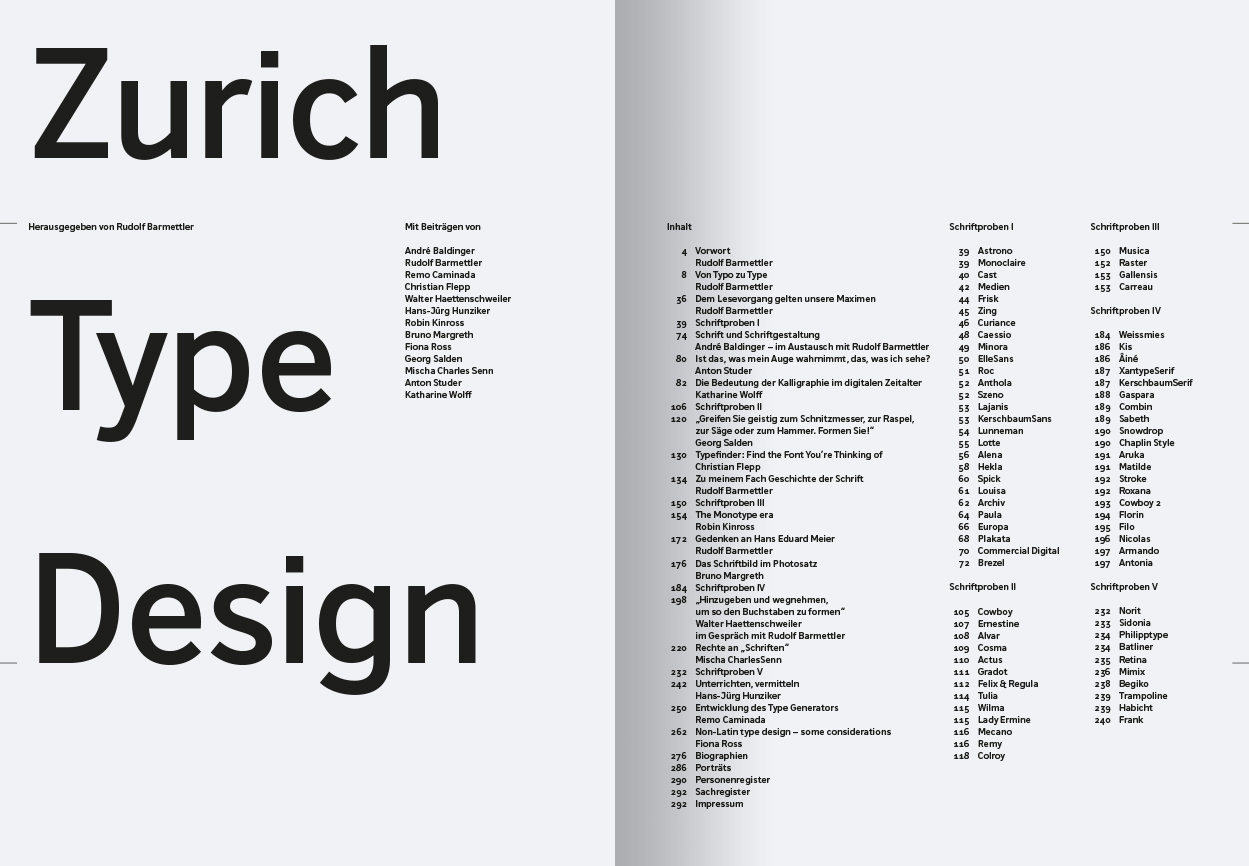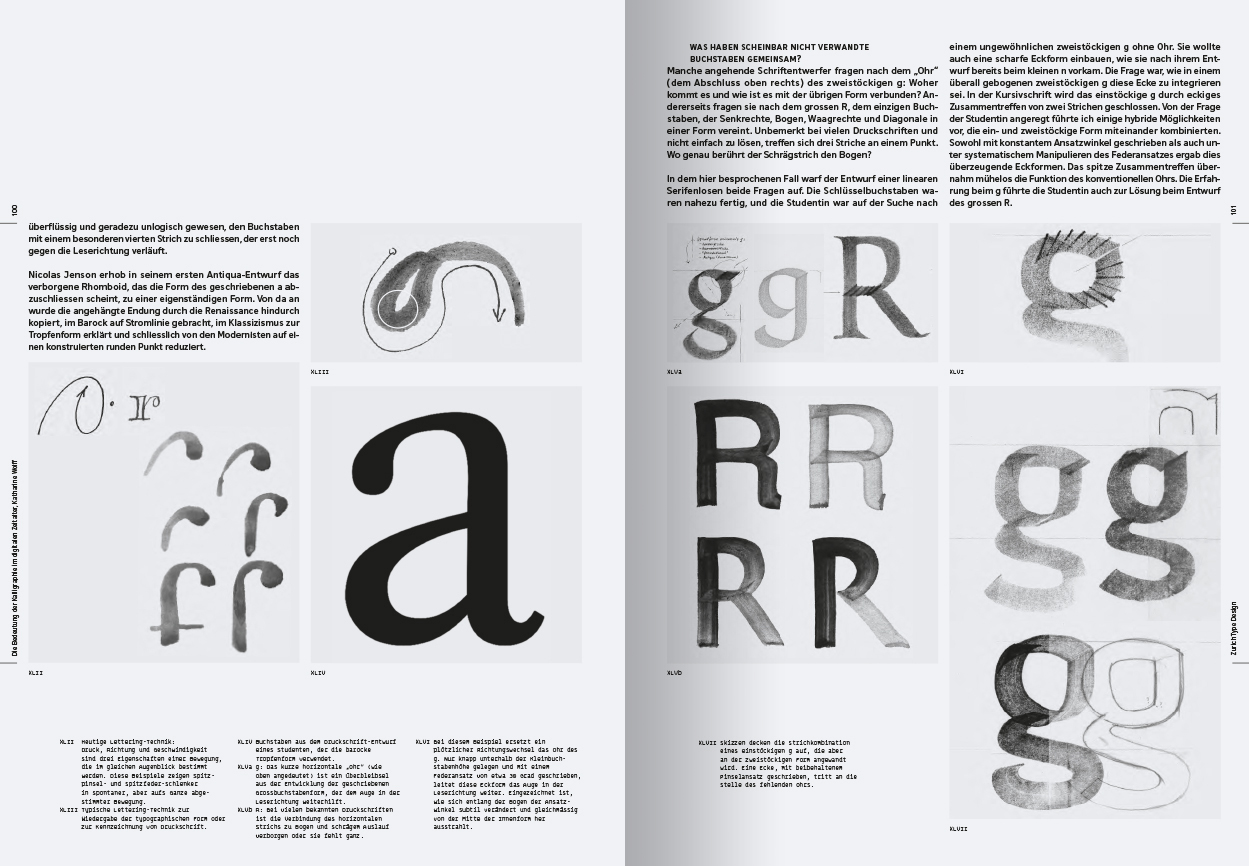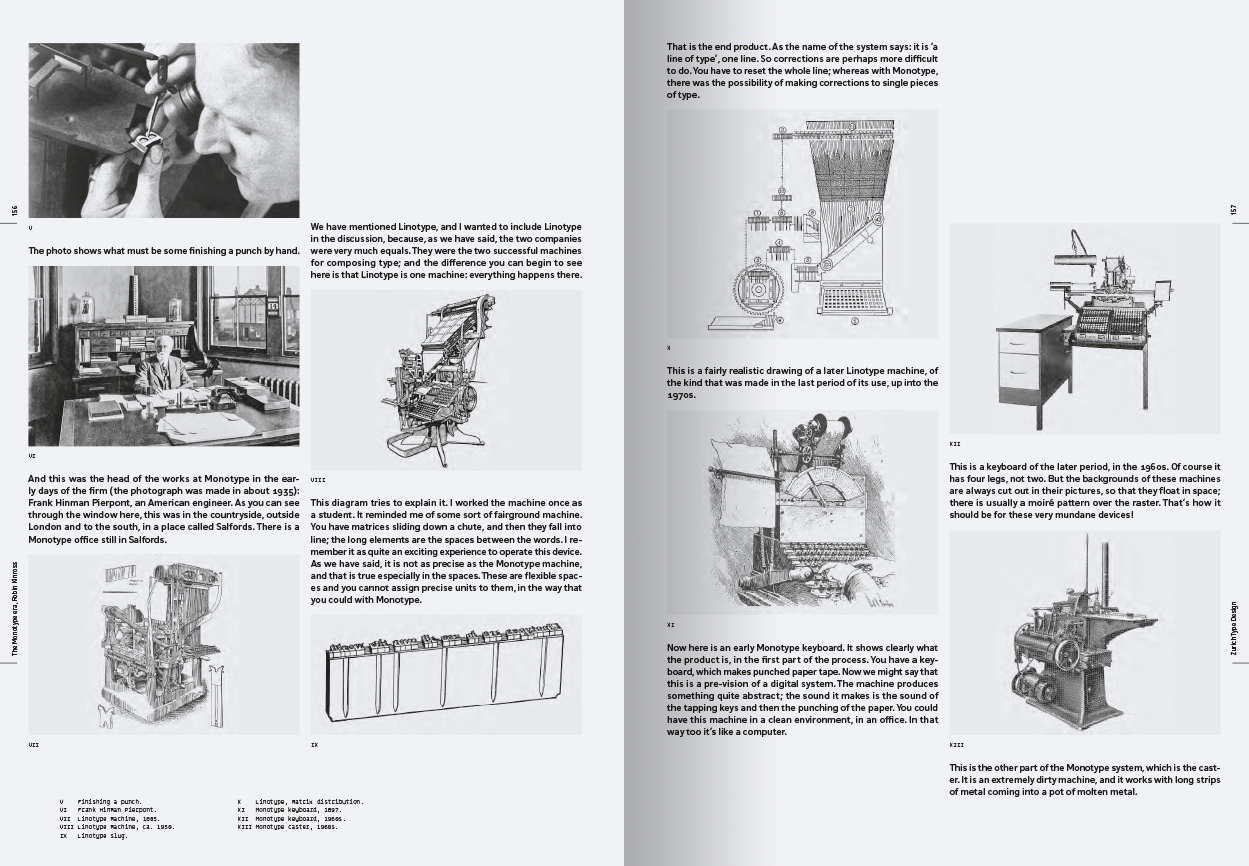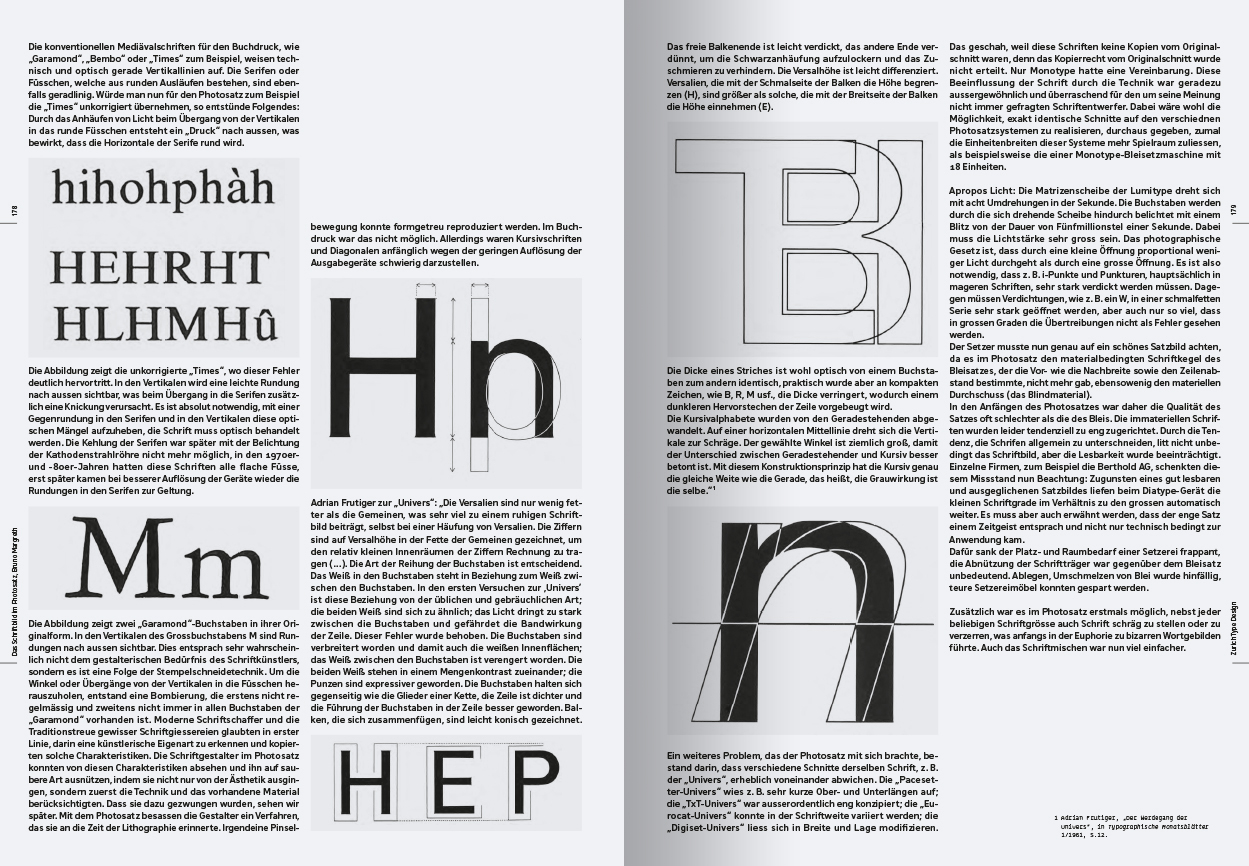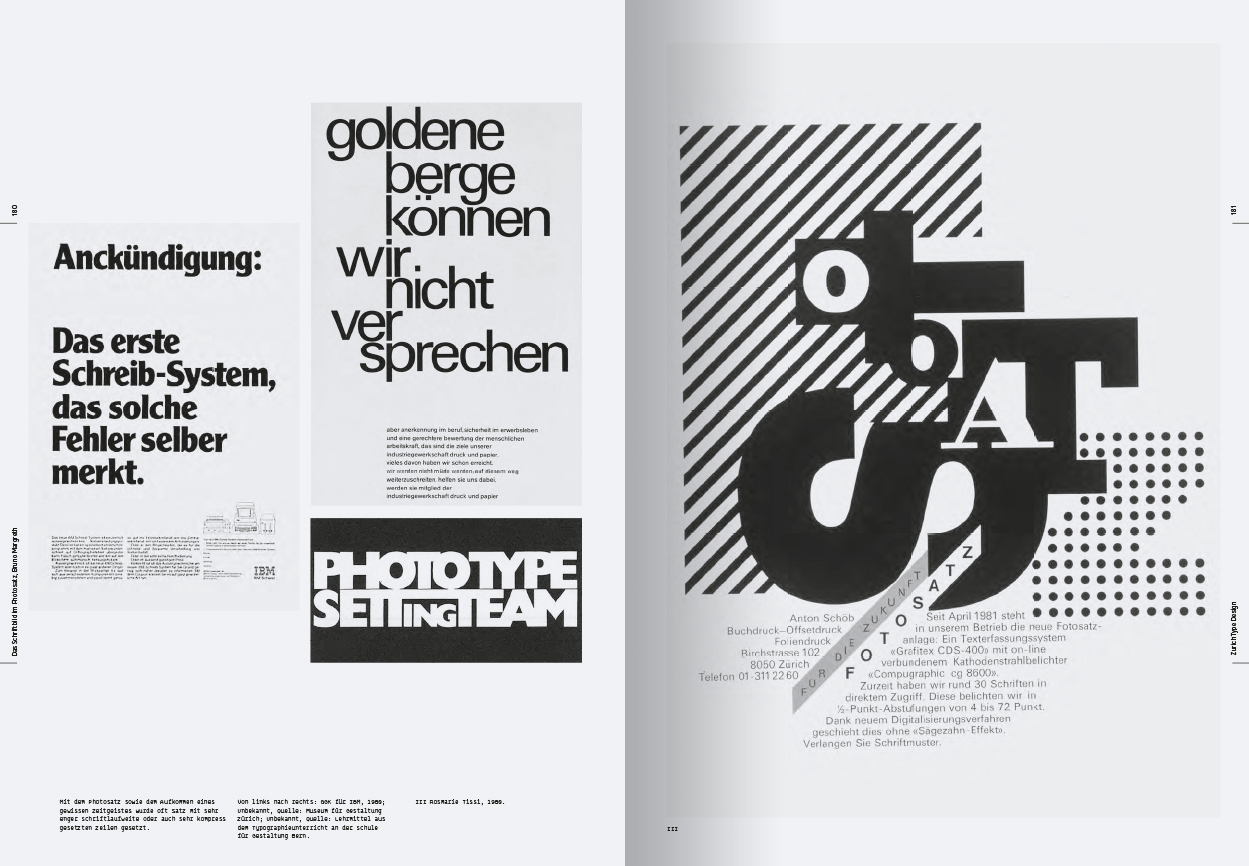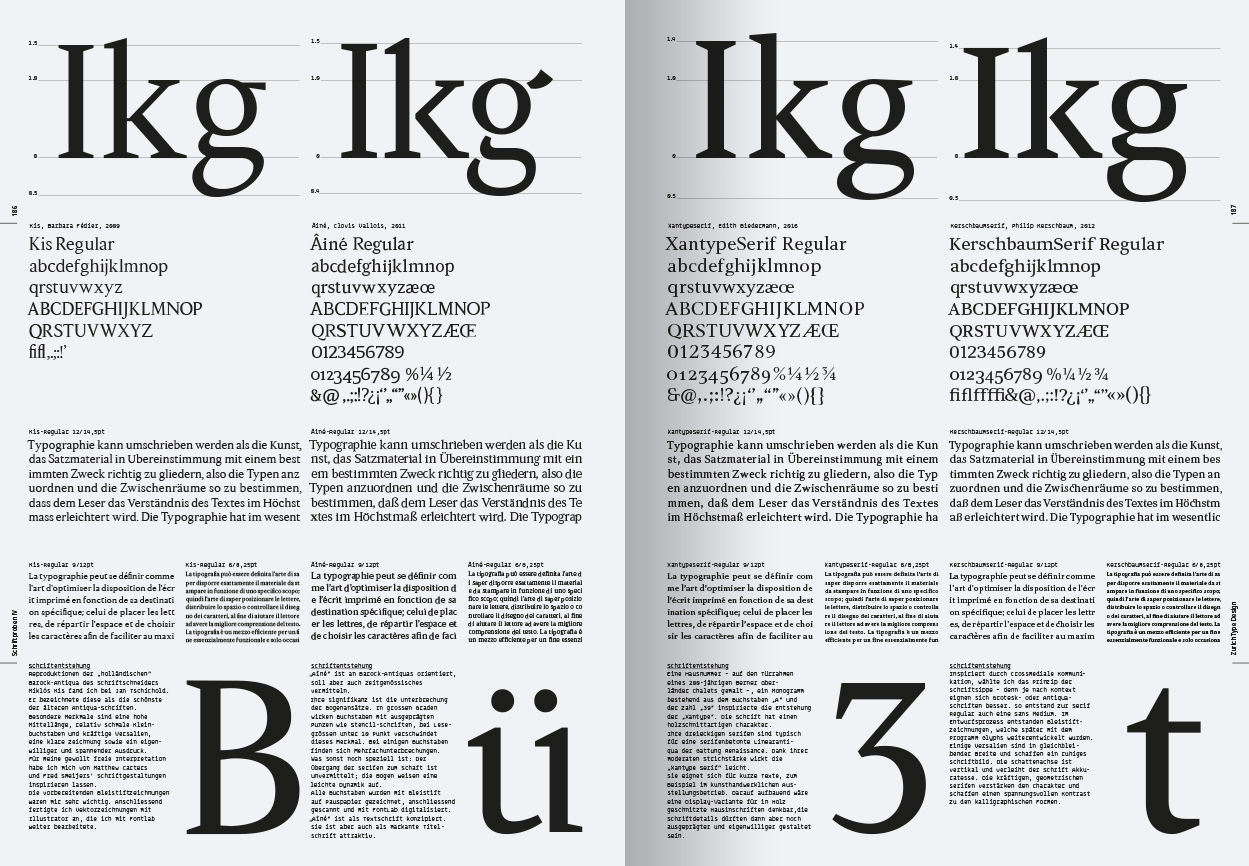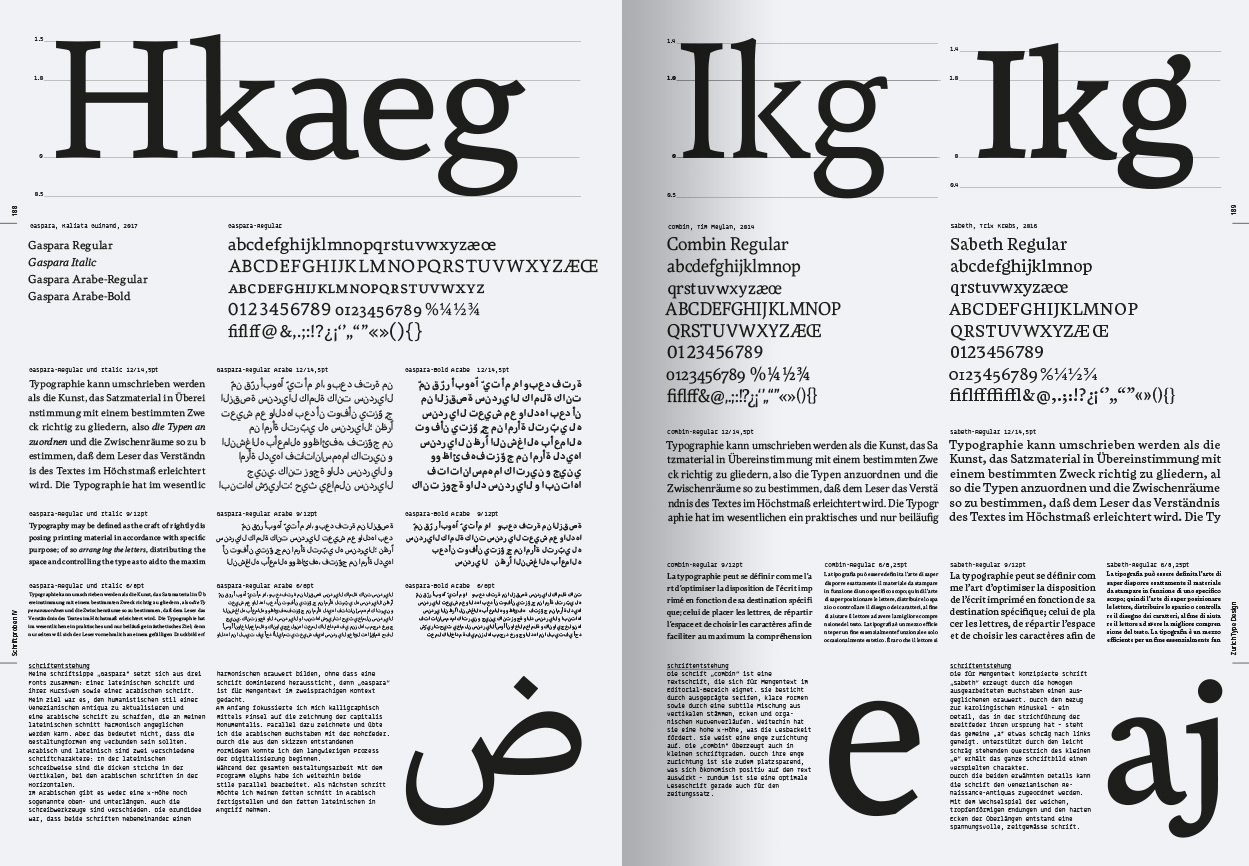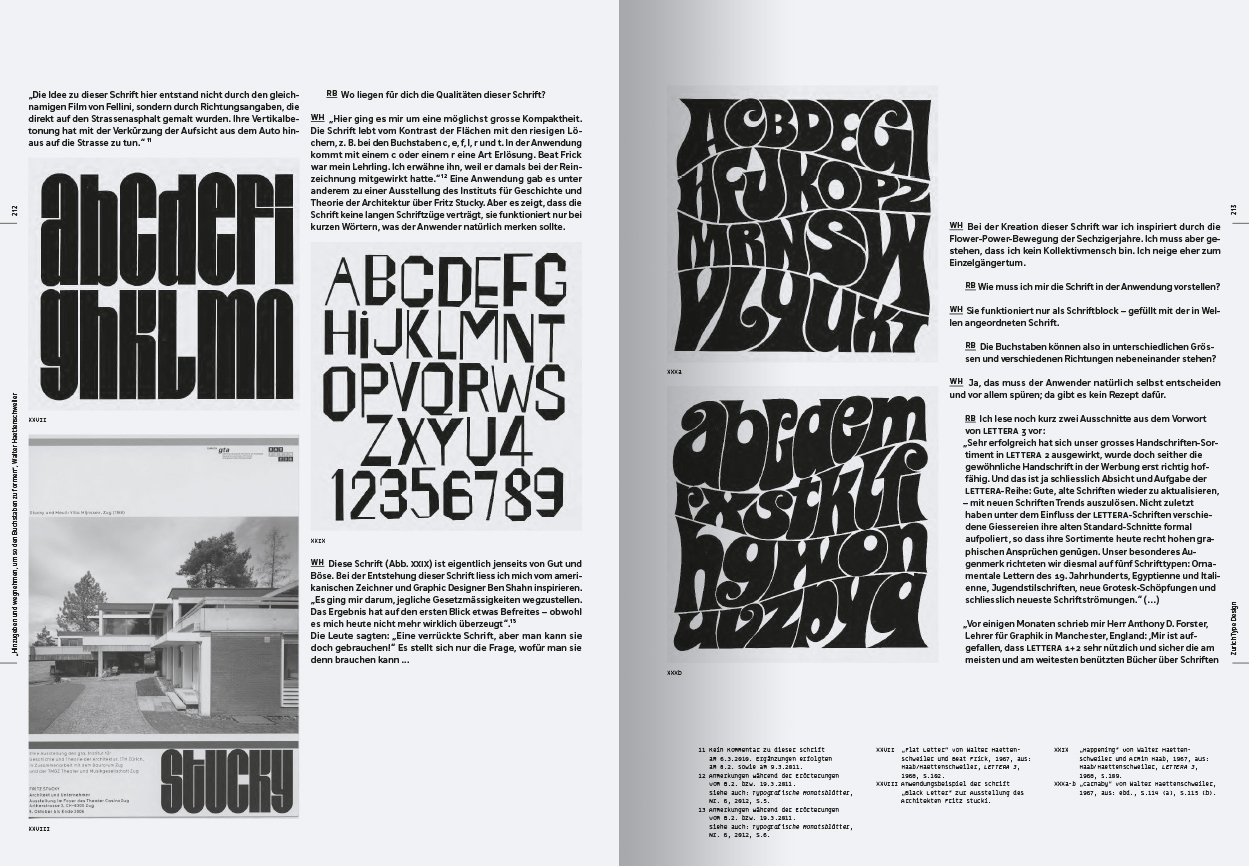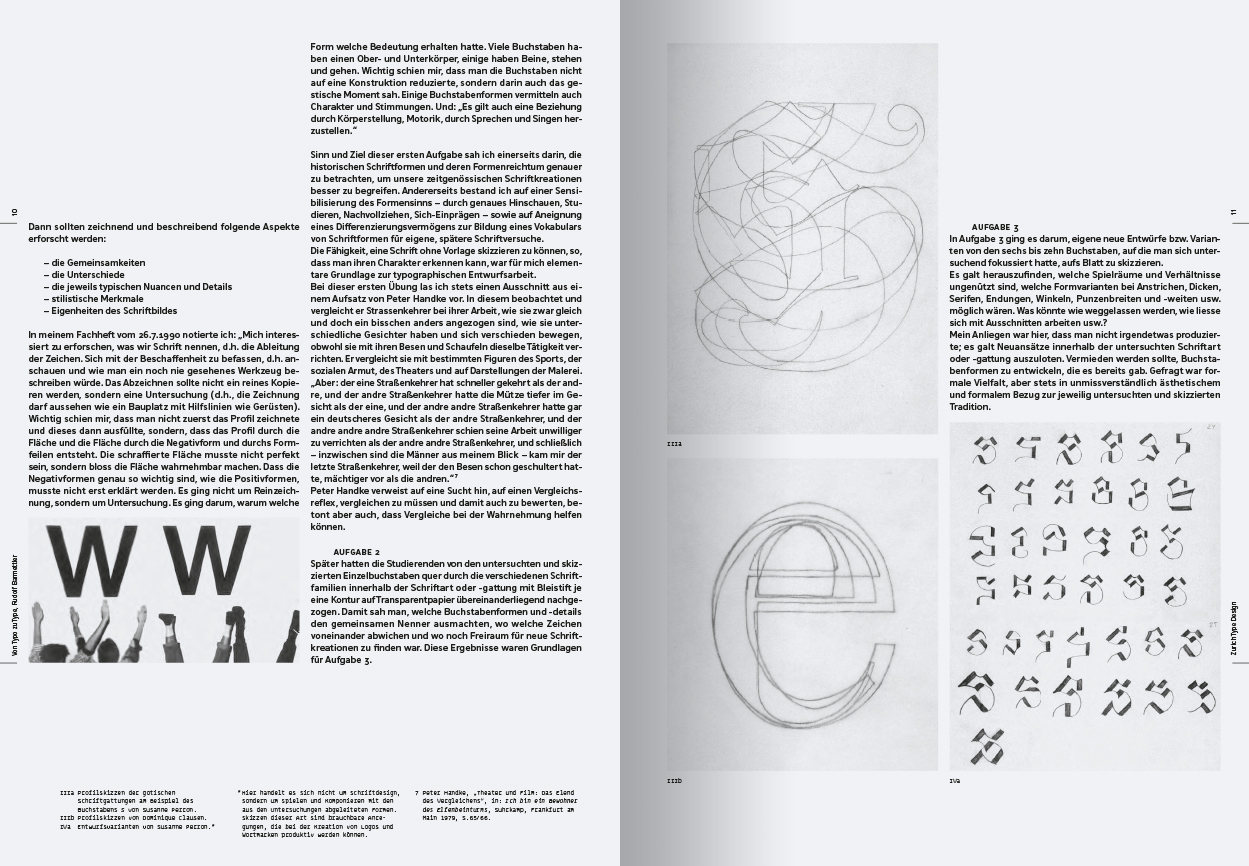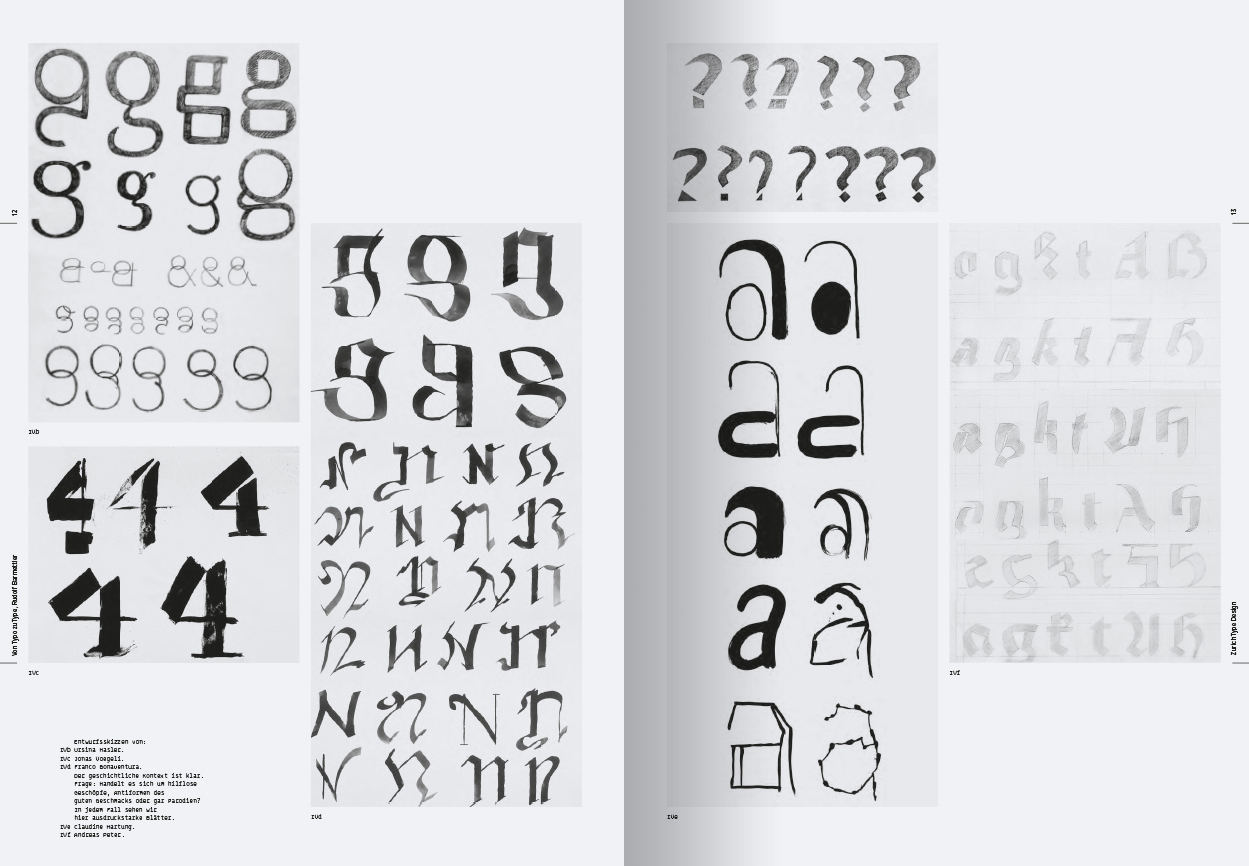
»Zurich Type Design«. Ein Fach- und Lesebuch für alle an Schrift Interessierten aus dem Triest Verlag in Zürich.
Ein typografischer Blick in die Schweiz lohnt immer: Helvetica, wohl die meist verwendete Schrift aller Zeiten, wurde bereits 1956 von Max Miedinger entworfen – auf den Schweizer Typografen Adrian Frutiger muß ich wohl auch nicht weiter eingehen …
An dieser Stelle möchte ich auf den 2015 in Zürich gegründeten Triest Verlag hinweisen, der sich mit einem umfangreichen Verlagsprogramm für Architektur, Design und Typografie präsentiert. Die beiden Gründerinnen Andrea Wiegelmann und Kerstin Forster haben es sich zur Aufgabe gemacht, gut gestaltete und hochwertig produzierte Fachbücher aus den Bereichen Architektur, Design und Typografie zu verlegen.
Aktuell erschienen ist das Fach- und Lesebuch »Zurich Type Design«, dass ich hier mit einigen Probeseiten vorstellen möchte. Herausgegeben wird es von Rudolf Barmettler, der an der Zürcher Hochschule für Künste das Fach Typografie lehrt.
Das Buch zeigt die Ergebnisse von über 70 neuen Leseschriften, die in Züricher Type-Design-Kursen entstanden sind. Dabei berücksichtigen die Entwürfe die besonderen Merkmale der Lesewirkung von Schrift, die gleichermaßen für Print wie auch für Screen Design gelten.
Spannende disziplinübergreifende Essays zu Lesbarkeit, Schriftgeschichte oder Schriftgestaltung, die von namhaften Grafik- und Type-Designer:innen verfasst sind, ergänzen dieses Fachbuch zu einem Lesebuch.
Zurich Type Design
Ein Fach- und Lesebuch
Hrsg.: Rudolf Barmettler
Hier einige Einblicke in das neu erschienene Fach- und Lesebuch: